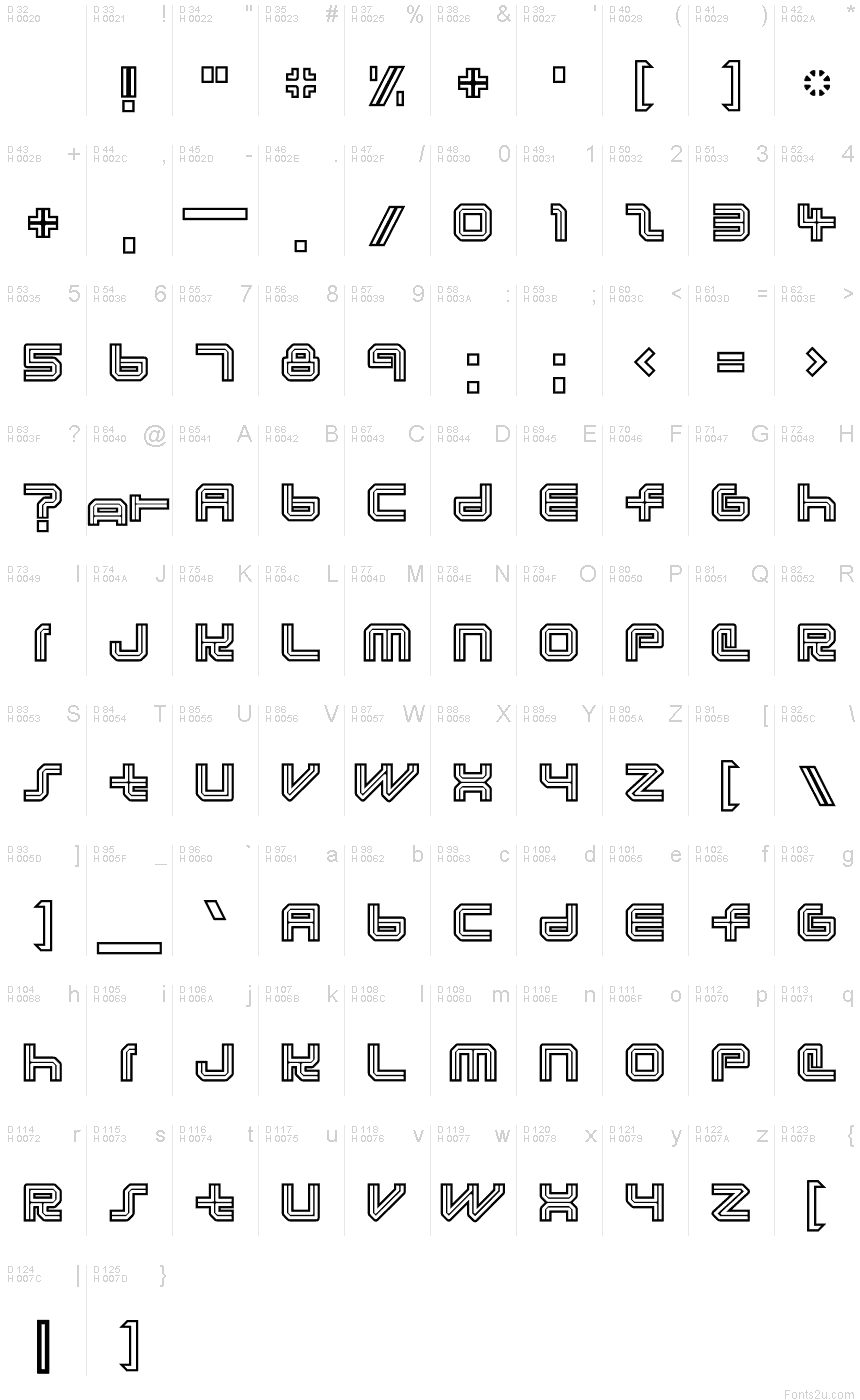
Lunaurora autorstwa Raya Larabie to bezpłatny, groovy font typu display, wyróżniający się zagnieżdżonymi, równoległymi konturami, które zmieniają każdą literę w zaokrąglony, prostokątny tor. Ta powtarzalna konstrukcja nadaje literom miękki, labiryntowy rytm, w którym kwadratowe narożniki i warstwowe pociągnięcia tworzą głębię bez konieczności stosowania cieni czy tekstur.
Ten krój świetnie sprawdzi się na okładkach płyt, plakatach festiwalowych, w brandingu w stylu arcade, na opakowaniach czy w dużych nagłówkach menu, gdzie pętelkowa struktura przyciąga uwagę bardziej niż zwykłe blokowe litery. Krótkie hasła i logotypy również na tym zyskują, ponieważ stos konturów tworzy dekoracyjną sylwetkę, która wygląda na gotowy projekt, zanim jeszcze zostaną dodane jakiekolwiek efekty.